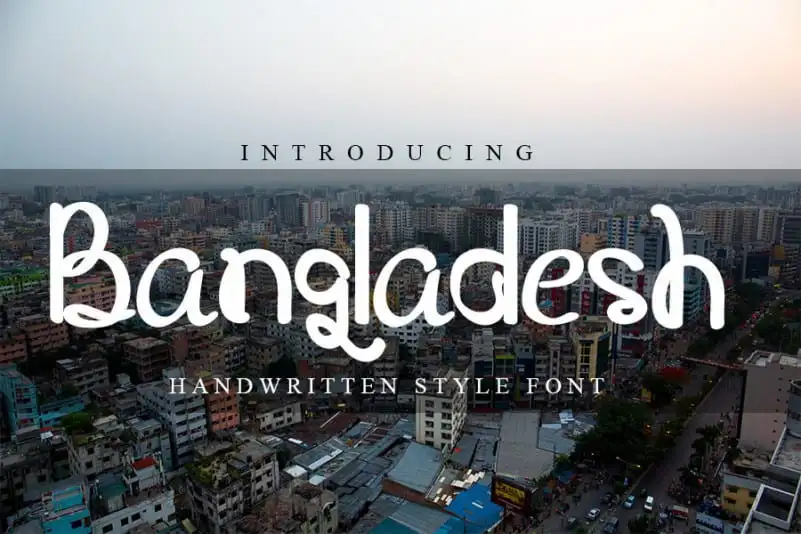
Bangladesh Script Font – Download Grátis
A Bangladesh Script Font é uma elegante escolha para designers que buscam mesclar influências chamativas do calligrafia com um toque contemporâneo e atual. Esta fonte script não apenas mantém sua sofisticação, mas também oferece a capacidade de se adaptar a diversos usos criativos como cartazes, títulos em impressões digitais e materiais de escritório. Suas linhas delicadas e seus tracinhos exatos permitem que designers criem um conjunto único de identidades visuais, dando uma sensação de frescura ao mesmo tempo que mantém uma consistência elegante. Ideal para aqueles que buscam dar um toque diferenciado em seu design, a Bangladesh Script Font é a escolha perfeita para qualquer projeto de arte digital ou impressão.